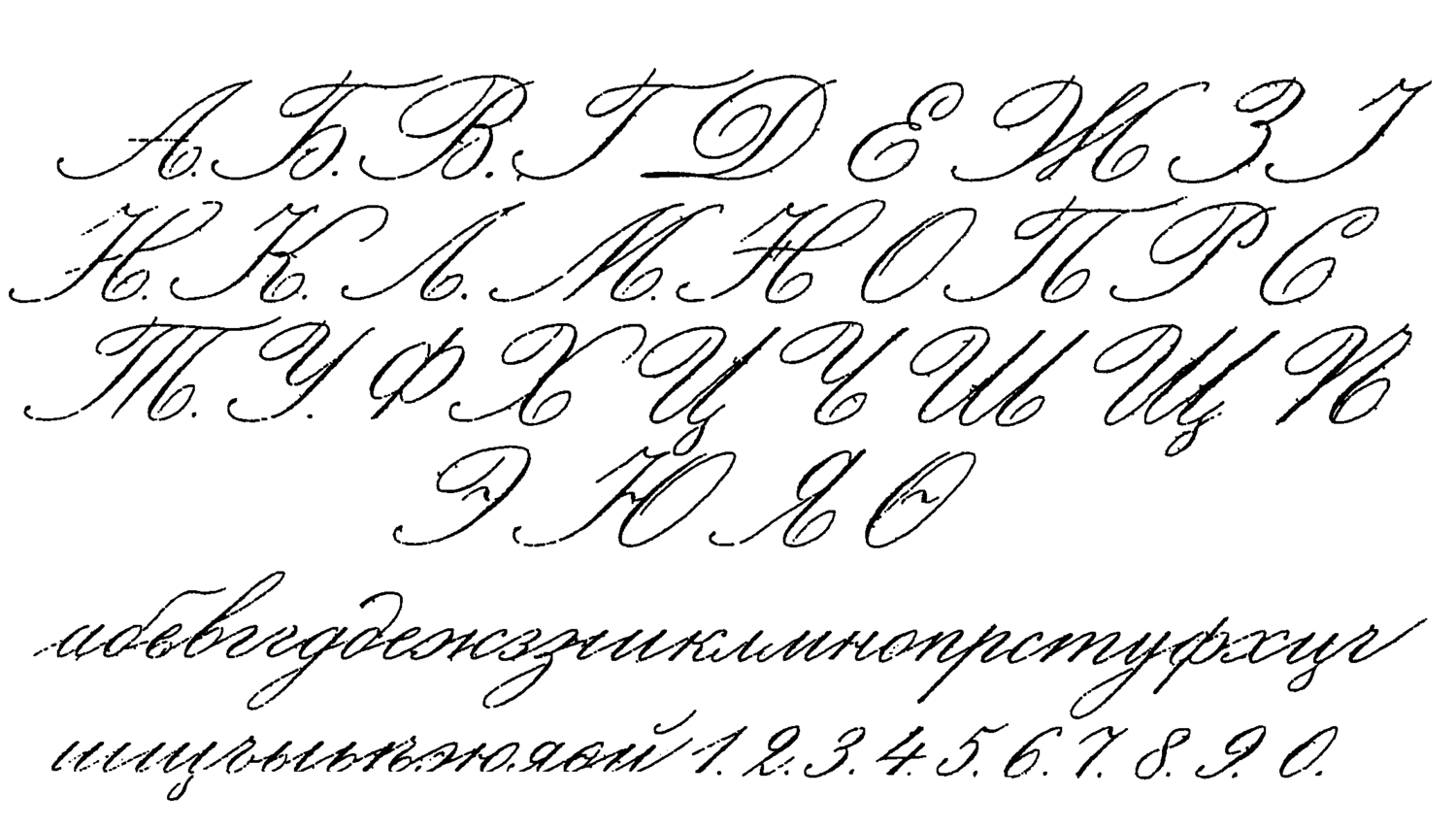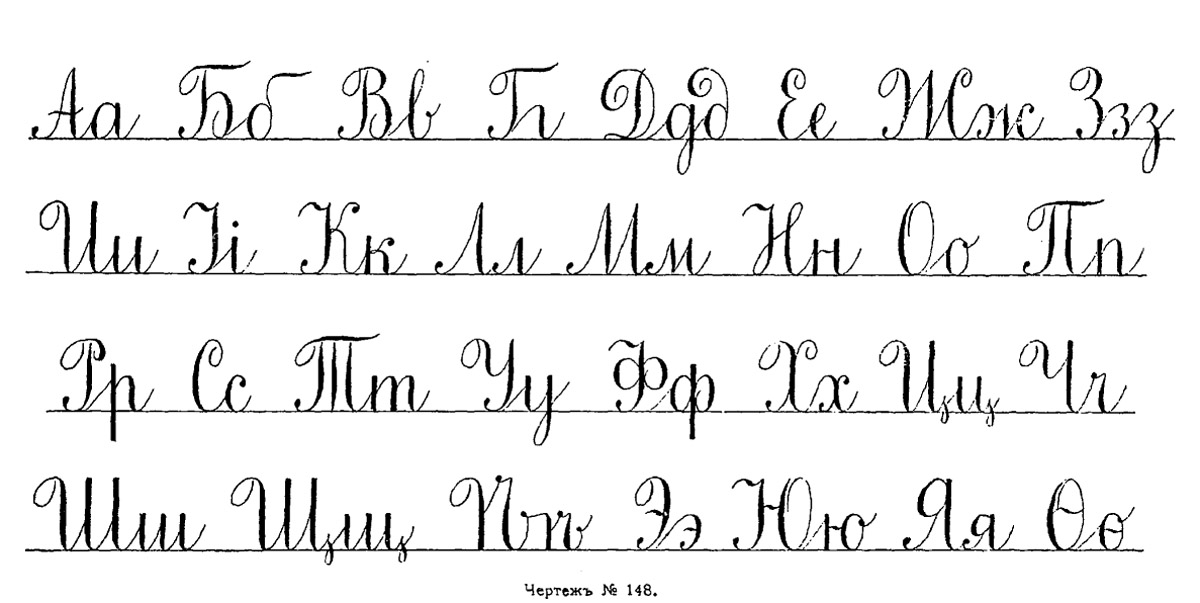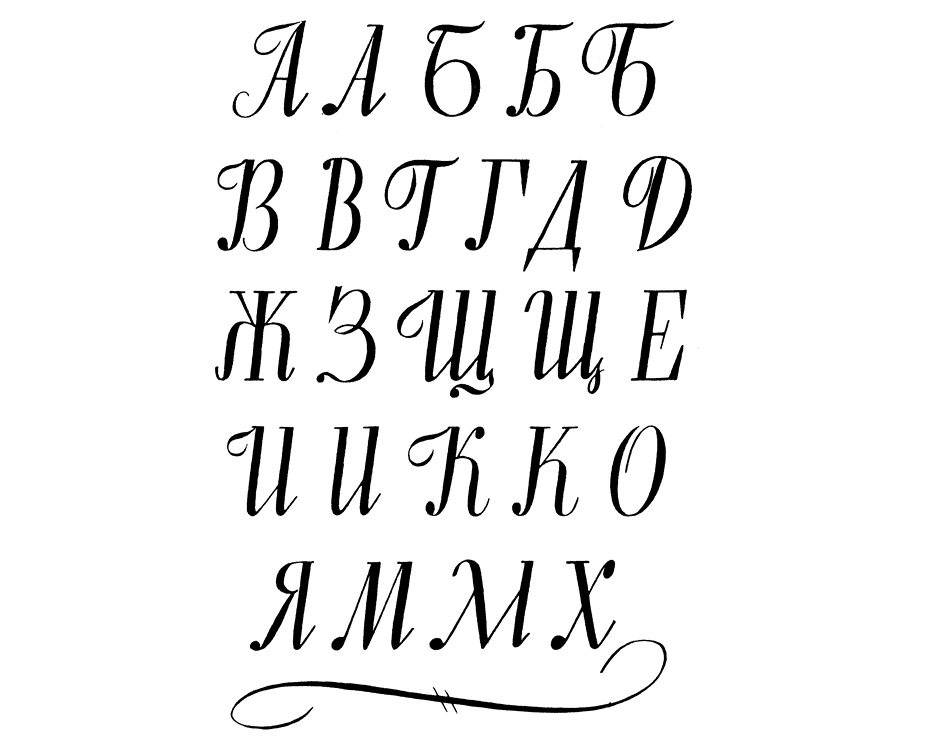
«Как подпись умирающего дедушки»: журналистку из США шокировал русский рукописный шрифт
«Поражена тем, что миллионы людей в состоянии это прочесть», — добавляет она.
Почерк врача давно стал мемом у русскоговорящих людей. Но как воспринимают наш рукописный шрифт иностранцы? На этой неделе журналистка Buzzfeed Данлелла Эмануэль опубликовала статью с заголовком «Я только что узнала, как выглядит русский рукописный шрифт, и поражена тем, что миллионы людей в состоянии это прочесть». В материале она собрала несколько мемов на эту тему и поделилась своими впечатлениями.
«Несмотря на то что мои предки были русскими, я не говорю на этом языке.
Думала о том, чтобы начать его учить, но недавно увидела на реддите нечто, лишившее меня энтузиазма. Представляю вам русский рукописный шрифт, — пишет она. — Почему это выглядит так, будто чей‑то умирающий дедушка оставил свою подпись на листе бумаги миллион раз?»